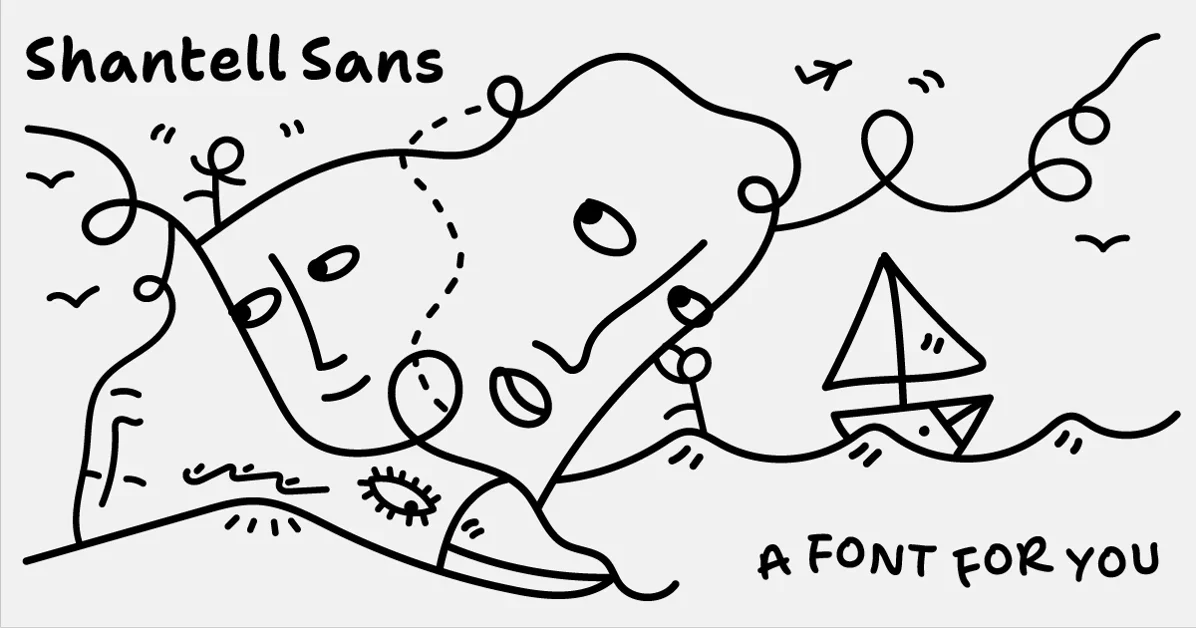
가변 폰트(Variable Font) 기술의 새로운 이정표 — Shantell Sans
Shantell Sans는 2023년 출시된 가변 폰트(Variable Font)로, formality slider라는 독특한 변수 축을 통해 폰트의 격식/비격식 스타일을 조절할 수 있음
일반적으로 새로운 폰트에서 취약하기 쉬운 키릴 문자(Cyrillic) 글리프를 Latin과 동일한 품질로 구현한 점이 주목받음
Comic Sans의 유산을 계승하면서도 보드체(Bounce) 효과와 자연스러운 곡선을 통해 더욱 진화된 디자인으로 평가받음
사용자들은 각 글자의 랜덤 변형(Variable Glyphs)을 통한 손글씨 같은 자연스러움을 바라는 목소리를 표시함
Formality Slider — 변수 축(Variable Axis)의 혁신적 활용
Shantell Sans의 가장 큰 기술 혁신은 formality slider라는 이름의 커스텀 변수 축이다. 일반적인 가변 폰트는 wght(weight), wdth(width) 같은 등록된 축만 지원하지만, 이 폰트는 폰트 디자이너가 정의한 커스텀 축(custom axis)을 통해 단일 폰트 파일에서 격식(formal)과 비격식(informal) 스타일을 연속적으로 조절할 수 있다.
기술적 구현: OpenType 변형(OpenType Variations) 스펙을 활용하여 글리프의 세밀한 변형을 정의
UX 관점: 사용자는 CSS의 font-variation-settings를 통해 폰트 특성을 동적으로 변경 가능
한계: 커스텀 축은 브라우저 지원 여부와 폰트 파일 내 구현 방식에 따라 성능에 영향 가능
결과적으로 이 기술은 폰트를 정적 리소스가 아닌 인터랙티브 디자인 요소(interactive design element)로 전환하는 패러다임을 보여준다.
키릴 문자(Cyrillic) 지원 — 글로벌 폰트 디자인의 과제
흥미로운 점은 Shantell Sans가 키릴 문자를 Latin과 동일한 품질 수준으로 지원한다는 것이다. 일반적으로 서양 기반 폰트 foundry에서 만든 신형 폰트는 키릴 문자의 특성(형태, 스트로크 굵기, 기울기)을 간과하는 경우가 많다. 이는 키릴 문자가 로마자와 구조적으로 다르기 때문이다.
ParaType(러시아 기반 foundry)과 같은 지역 foundry는 역사적으로 키릴 지원에 강점이 있었음
Shantell Sans의 글 작성에 따르면 키릴 최적화를 위해 별도의 글리프 설계 및 테스트 과정을 거쳤다고 언급
실무적 시사: 한국어(Korean), 중국어(Chinese) 등 Non-Latin 스크립트 지원은 여전히 과제이며, 이를 성공적으로 해결한 사례가 희소
결론적으로 다스크립트 지원(Multi-script Support)은 글로벌 웹 타이포그래피에서 중요한 고려사항이다.
Variable Glyphs — 랜덤 변형을 통한 자연스러움 추구
토론에서 주목할 점은 mercacona의 의견이다. 손글씨처럼 매번 같은 모양의 글자가 반복되면 읽기 피로(Reading Fatigue)가 발생한다는 것이다. 이를 해결하기 위해 각 글자에 5-6개의 변형을 정의하고 랜덤으로 적용하는 Variable Glyphs 개념을 제안했다.
현재 기술적 제약: OpenType의 변형 테이블(variation table)은 연속적인 값 변경에 초점, 불연속적인 랜덤 선택은 미지원
대안적 접근: CSS의 letter-spacing, word-spacing과 결합하거나, JavaScript 기반 랜덤 글리프 교체 구현 가능
성능 고려: 랜덤 변형은 텍스트 렌더링 시 추가 연산이 필요하며, 실시간 웹에서는 부담이 될 수 있음
결론적으로 Variable Glyphs는 기술적으로 가능하지만, 현재 웹 생태계에서 범용적으로 적용되려면 추가 표준화가 필요하다.
Comic Sans 유산과 보드체(Bounce) 효과의 진화
여러 댓글에서 Comic Sans와의 연결고리를 언급했다. Comic Sans는 1994년 Microsoft에서 발표된 폰트로, 원래 비디오 게임 타이틀용으로 설계되었으며, 이후 비공식적 콘텐츠에서 과도하게 사용되어 "저품질 타이포그래피"의 상징이 되었다. Shantell Sans는 이 유산을 계승하면서도 차별화한다.
보드체 효과: 글자의 세로 방향 흔들림을 통해 손글씨의 자연스러운 리듬감을 재현
자연스러운 곡선(Spontaneous Curves): 직선 구조를 최소화하여 유기적 흐름(Organic Flow) 구현
핵심 차별점: Comic Sans의 "형식 없음"과 달리, formality slider를 통해 격식/비격식 조절 가능
결과적으로 Shantell Sans는 레거시 폰트의 한계를 극복하고 "설계된 자연스러움(Designed Naturalness)"을 제공한다고 평가받는다.